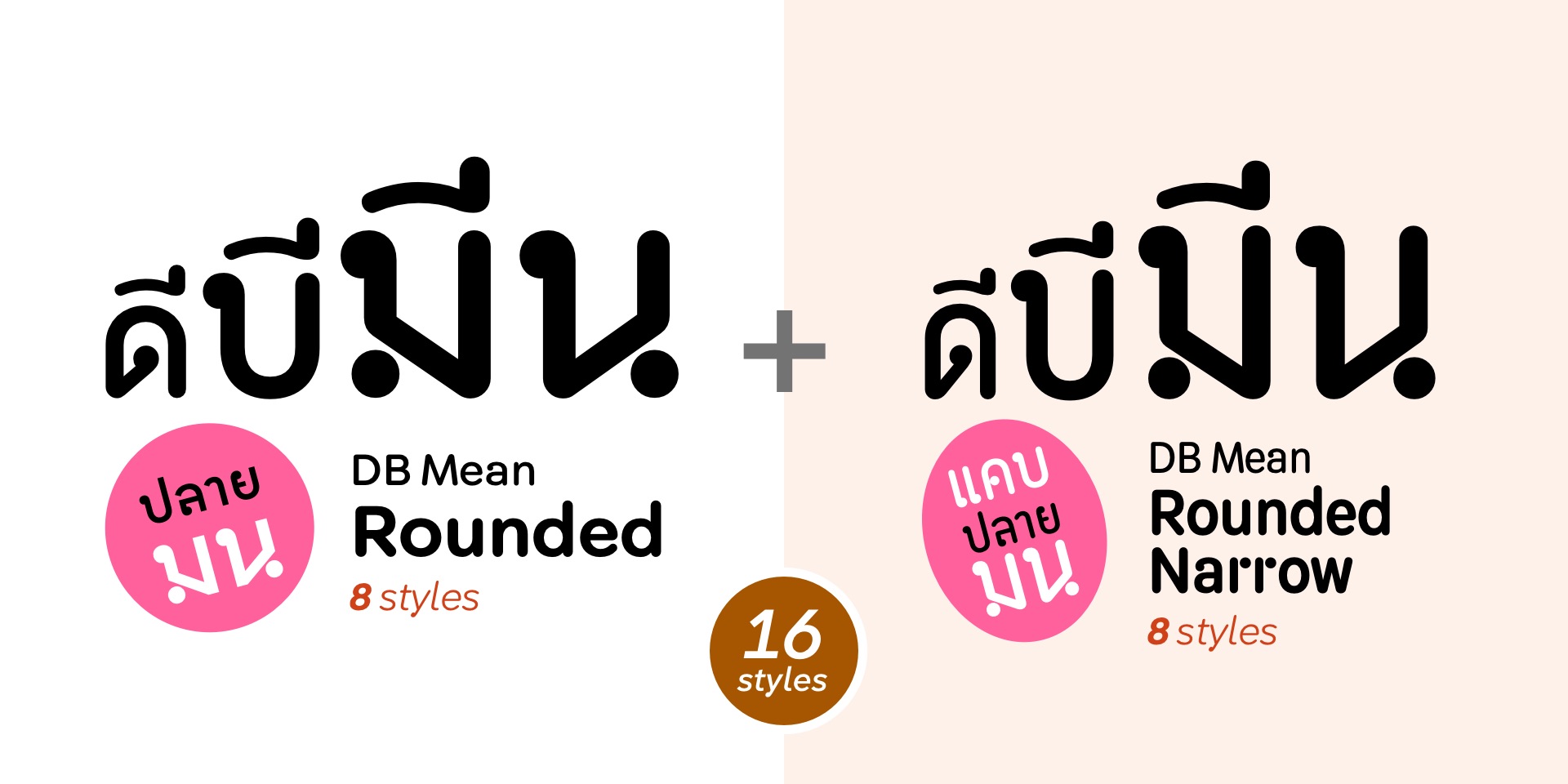
DB Mean Rounded Bundle
ดีบี มีน ปลายมน
2 font families,
16 styles
รวมชุด ฟอนต์
DB Mean Rounded และ DB Mean Rounded Narrow
ปลายมน, ตัวกว้างปกติและตัวแคบ
ที่เป็นตัวพาดหัวก็ได้ เป็นตัวพื้นก็ดี
2 font families
ดีบี มีน ราวนด์
8
styles
ดีดี มีน ราวนด์ แนโรว์
8
styles